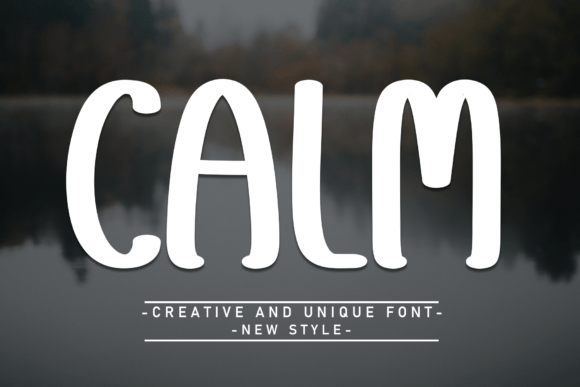
Calm
適切なデザイン要素を見つけるのは難しい場合がありますが、Calmは作品を即座に引き立てる優れたコレクションを提供します。
精密に作られたCalmは、クリーンなベクター、滑らかなタイポグラフィ、そして安心のための商用ライセンスを提供します。
POD(オンデマンド印刷)製品、結婚式の招待状、またはソーシャルメディアのグラフィックを作成している場合でも、Calmは理想的です。